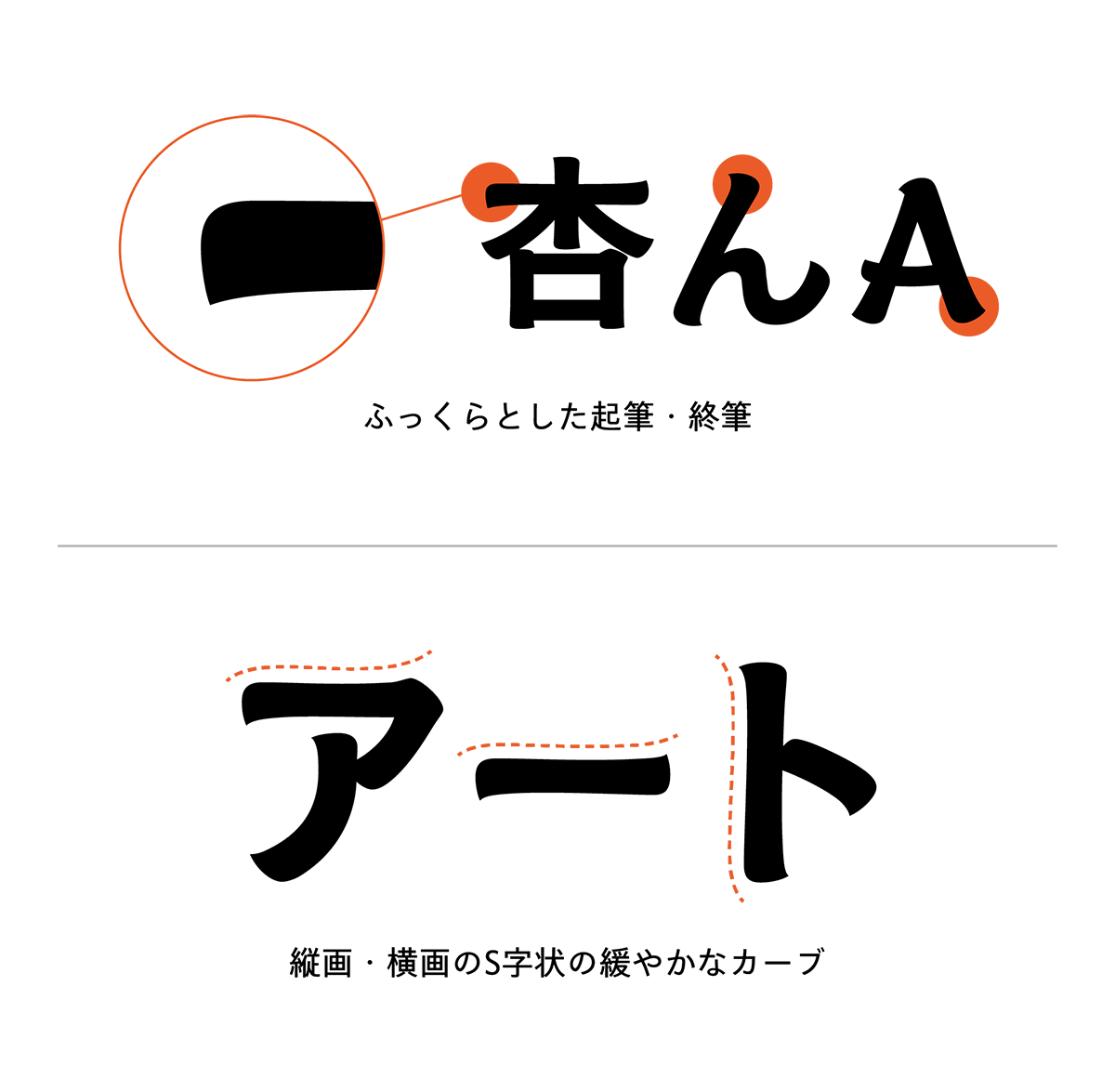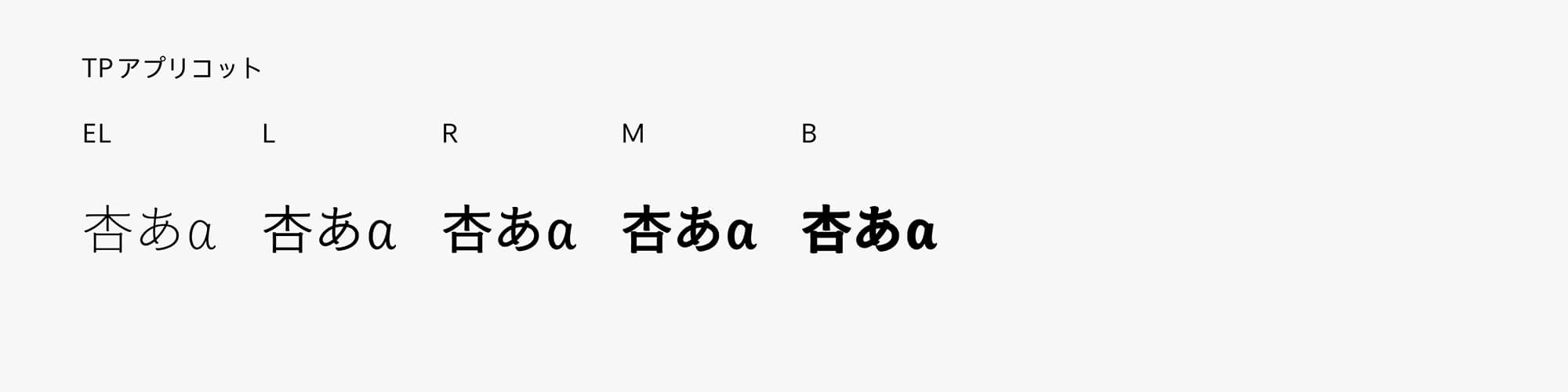
タイププロジェクト、みずみずしい果実からしたたる雫がモチーフの「TPアプリコット」を発表
もぎたての果実を思わせる「シズル感」をまとった筆書系書体
TPアプリコットのふっくらとした起筆・終筆の形は、みずみずしい果実からしたたる雫をモチーフに、筆圧の変化による線幅やインクの流れを反映させたデザインです。手書きの風合いを取り入れ、個性と読みやすさを両立するデザインを目指しました。抑揚のある線質と丸みを帯びたパーツが持ち味で、筆やフェルトペンなどの筆記具で描く線を想起させる形状を随所に取り入れています。画数の少ない欧文や仮名では起筆・終筆の膨らみなどのメリハリを強め、線の混み合う漢字では抑揚を抑えることで、書体全体のバランスを整えています。縦横のストロークにはS字状の緩やかなカーブを持たせ、ゆっくり線を引くときの手と筆記具の滑らかな動きを表現しています。
TPアプリコットの漢字はウェイトごとに骨格が異なるのが特徴です。太いウェイトでは起筆・終筆の膨らみやウロコなど黒味の強い要素が多いため、懐をやや広めにとり、やわらかくふっくらとした印象に仕上げています。反対に、細いウェイトではストローク間の空間が広がるため、太いウェイトに比べて懐が大きく見えすぎないよう全体を引き締めています。
タイププロジェクトの代表取締役 鈴木 功は、「TPアプリコットは、手書きの風合いと高い実用性を両立させた新鮮味あふれる書体です。有機的なストロークと端正な骨格を融合させ、漢字・仮名・欧文それぞれの持ち味を大事にしつつそれらが混じり合ったときの絶妙な香りの調和を企図しました。書籍のタイトルから飲料・食品のパッケージまで、みずみずしさやあたたかみが期待される場面で効果を発揮すると自負しています」と述べています。
TPアプリコットは、EL(エクストラライト)、L(ライト)、R(レギュラー)、M(ミディアム)、B(ボールド)の5ウエイトで提供します。